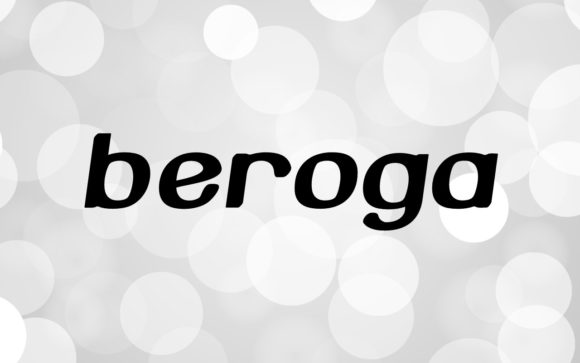
Beroga
Beroga – A Fonte Criativa que Transforma seus Projetos
Se você está em busca de uma tipografia que una criatividade, versatilidade e estilo, Beroga é a escolha ideal. Criada por Peter Wiegel, esta fonte display se destaca por seus caracteres adaptáveis, capazes de se encaixar perfeitamente em diferentes estilos de design, do mais minimalista ao mais ousado.
- Design inovador: formas únicas que dão personalidade instantânea a qualquer peça.
- Versatilidade: funciona bem em logotipos, cartazes, embalagens, websites e até em projetos de branding.
- Legibilidade equilibrada: apesar de ser uma fonte display, mantém clareza mesmo em tamanhos menores.
Por que Beroga é a Escolha Certa para seu Próximo Projeto?
Adicionar Beroga ao seu arsenal criativo significa dar vida às ideias com um toque de modernidade e elegância. Seu estilo “cool” e ao mesmo tempo profissional a torna perfeita para:
- Campanhas publicitárias que precisam chamar atenção.
- Identidades visuais de marcas que buscam se diferenciar.
- Designs de embalagens que contam uma história visual.
- Sites e landing pages que desejam uma tipografia marcante.
Em resumo, Beroga é a fonte display que combina criatividade e adaptabilidade, permitindo que designers de todos os níveis elevem seus projetos a um novo patamar. Experimente agora e descubra como ela pode trazer vida às suas ideias mais ousadas.